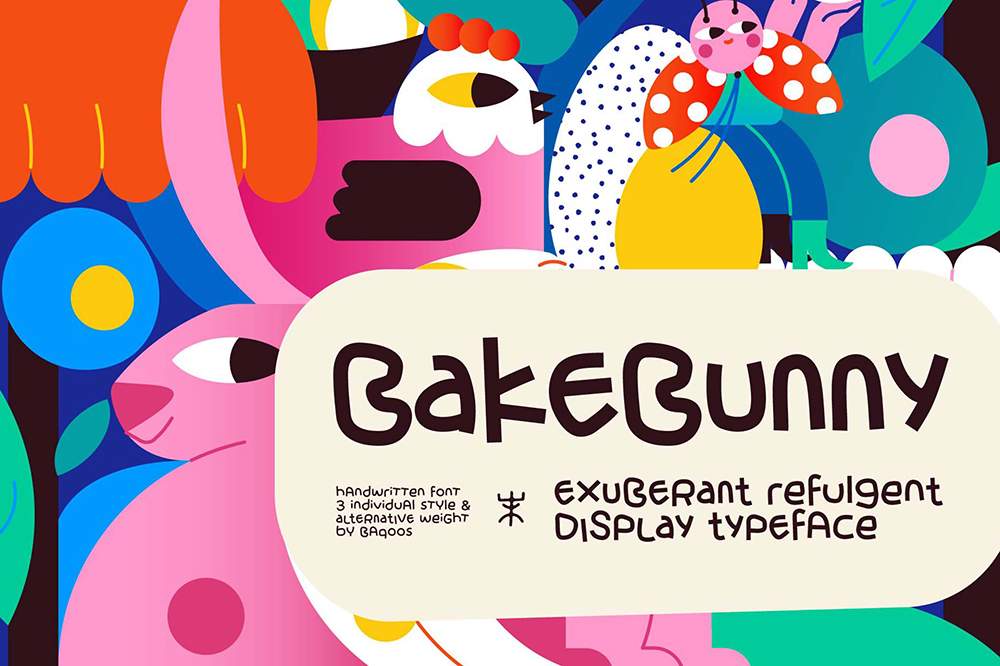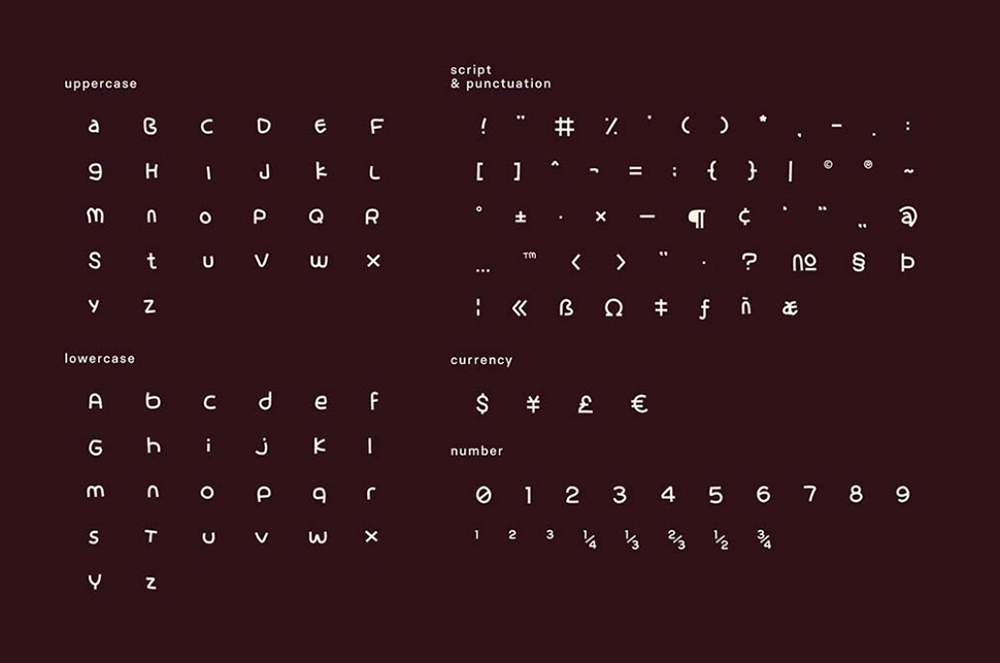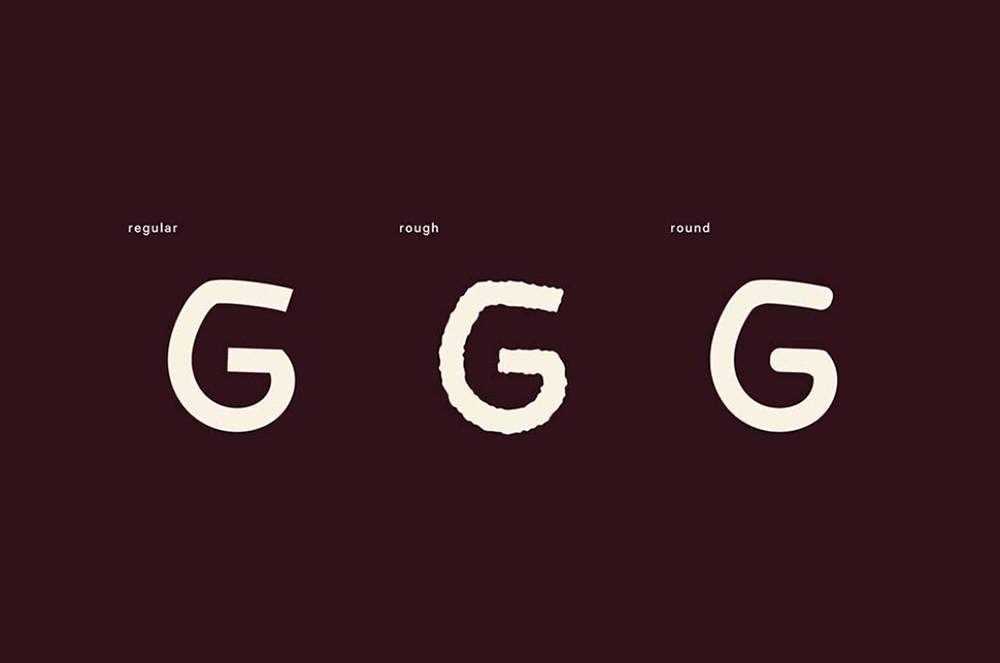
دانلود فونت انگلیسی Bake Bunny Font
فونت پرمیوم و انگلیسی Bake Bunny Font یک فونت دستنويس، چرخ و فلکی شاد از حروف است که با روحيهای بازيگوش و جذابيتی شيطنتآميز میچرخد و نگاهها را به خود جلب میکند. فونت Bake Bunny با مجموعهای گسترده از بيش از 200 علامت شامل علائم نگارشی و اعداد، تطبيقپذيری آن به اندازه حس بازيگوشیاش مسحورکننده است. از دعوتنامهها گرفته تا لوگوهای برند و… و روی بوم تخيل شما میپرد.
مزایای استفاده از فونت لاتین Bake Bunny چیست؟